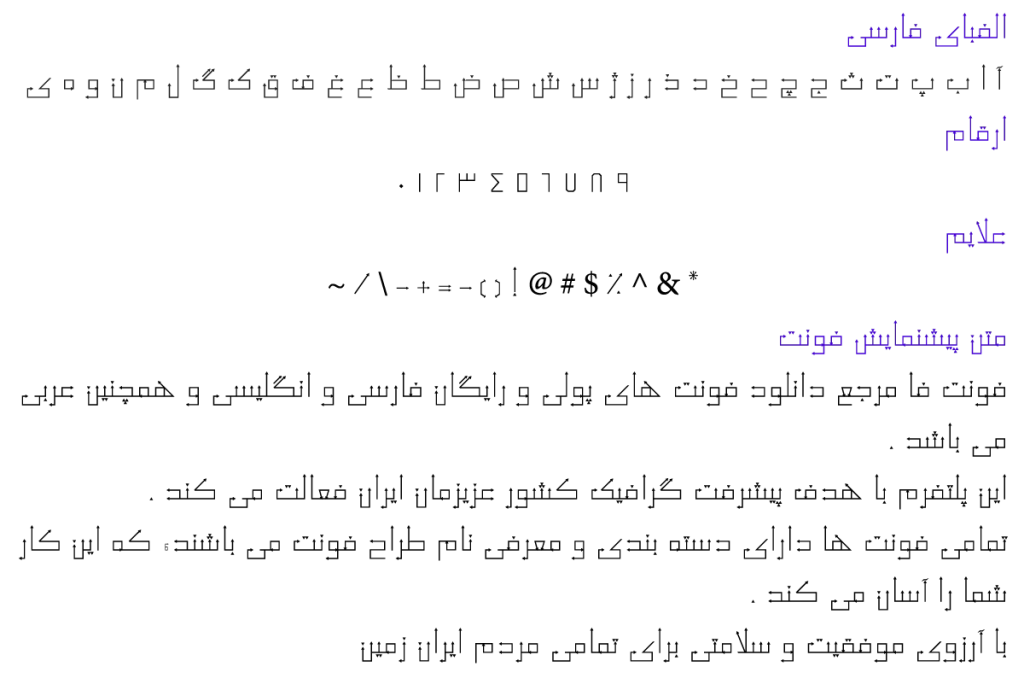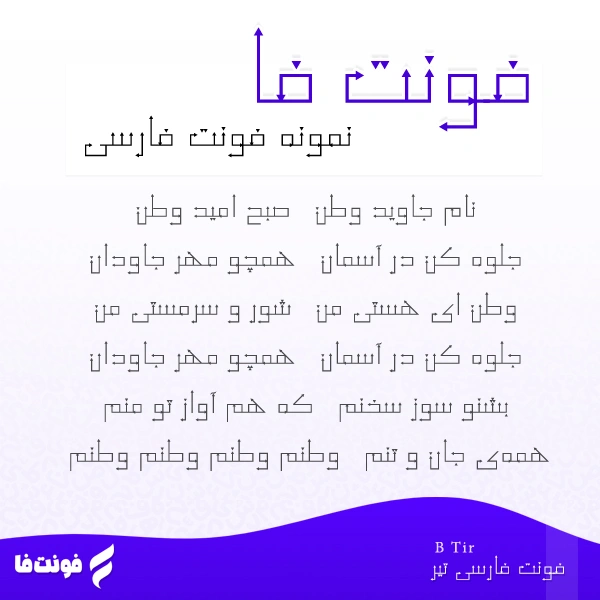
فونت فارسی تیر – B Tir
سال ساخت فونت: 1379
مجموعه فونت: فونت سری B
طراح فونت: برنا رایانه نوع فونت: فونت هندسی
پیشنمایش فونت بی تیر
توضیحات و معرفی فونت تیر
فونت فارسی تیر ( B Tir ) از مجموعه فونت های سری B می باشد، همینطور نوع فونت هندسی می باشد.
فونت زیبای مرتبط توسط برنا رایانه در سال 1379 طراحی و ساخته شده است.
در تصویر زیر، پیش نمایشی از این تایپ فیس را همراه با شعر زیبای فارسی میبینید.